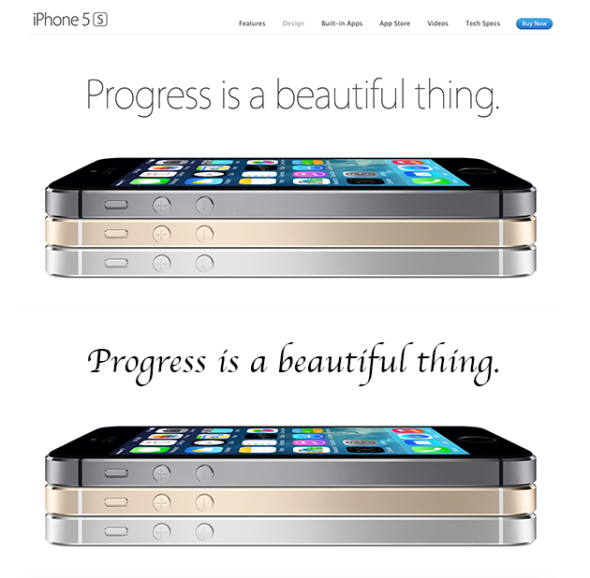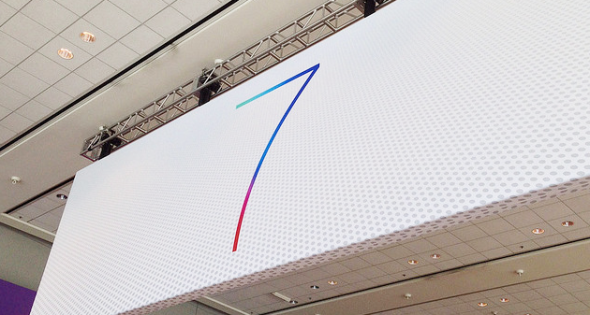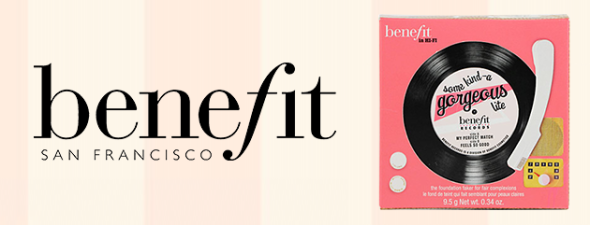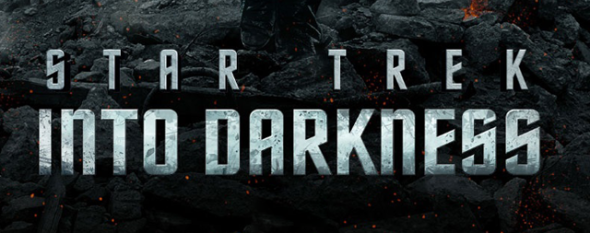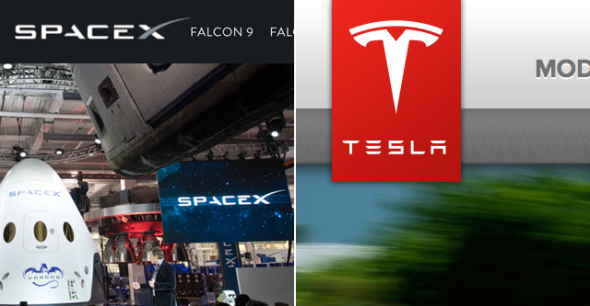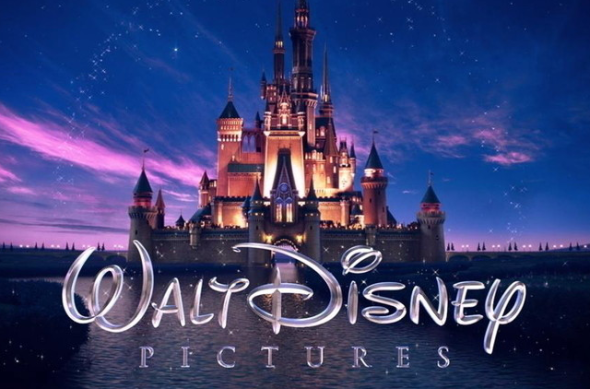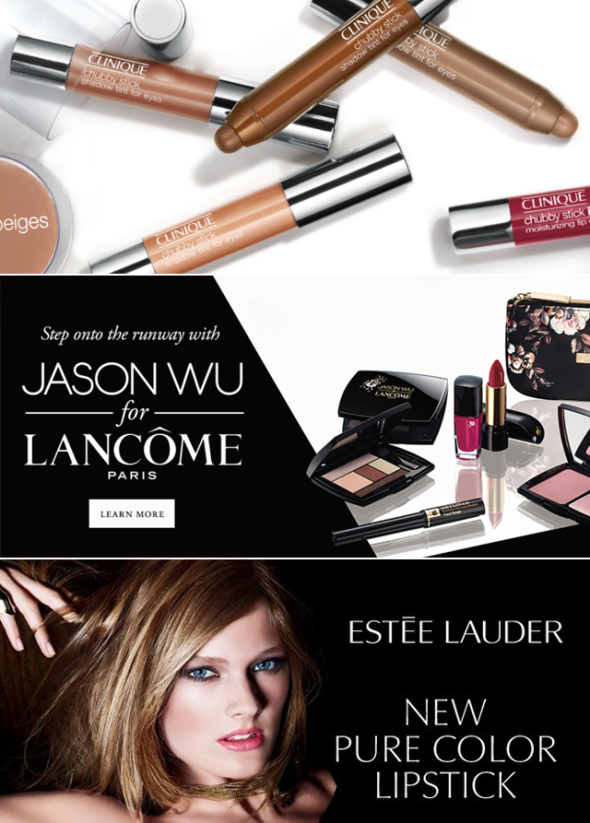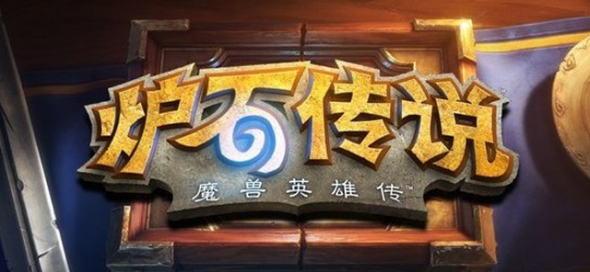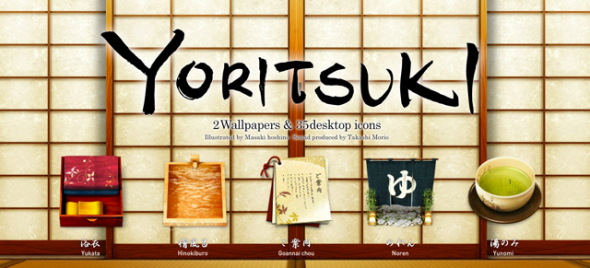
当我们拿到一款产品的包装或者登入了一个网站的时候,你是否会有意或者无意地留意到属于这个产品的特定的字体设计或者使用,从而影响到你对这个产品最直观的感受。精致、优雅、科幻、古典或者是觉得粗糙难看呢?
比如当我把苹果网站上 iPhone 的字体换掉以后,你一定或多或少的察觉到了什么不一样的地方,也许你无法表达出来或者无法说出究竟是哪里出了问题,但这潜意识的感受正是不同字体风格传递给用户的直观感受所造成的。因此在给一个产品选择或者设计字体的时候,除了你需要考虑其易读性,一定也需要考虑这款字体是否能准确地传递给消费者或用户属于这款产品的独特气质。
A.现代
现代风格字体多为无衬线字体,这类字体除本身文字的比划之外缺少装饰性的元素,风格较简约。
WWDC 2013前夕,即便在 iOS 7 并未对外界正式发布之前,但是通过会场的海报人们都清楚地意识到,iOS 7 的风格一定带来了极大的转变。Helvetica Neue 风格非常现代,似乎暗示着苹果将在 iOS 7 中完全剔除过去人们陈旧的审美,取而代之的是更为现代的视觉风格,而在后来的大会上 iOS 7 的最终发布也证实了这种观点。
B.复古
化妆品品牌 Benefit 诞生于美国上世纪 70 年代这个自由奔放的时代,而创始人之一的姐姐 Jean Ford 刚好主修艺术,她十分懂得如何包装她们的品牌。Benefit 的包装和字体颇具复古风,比如留声机造型的包装盒。衬线字体的 logo 具有较强的装饰性,字母的转角处线条柔和,更具流线形的字母 f 使 logo 显得更生动有趣,搭配留声机造型内部的连笔手写体,一股浓浓的复古风扑面而来,见到如此有趣又漂亮的包装盒,难怪让很多女性爱不释手。
C.科幻
电影星际迷航的海报上的字体就属于这种类型。实际上我们经常会在一些科幻电影的海报或者网站上见到这种类型的字体。科幻风格的字体风格普遍比较硬朗和锐利,通常有过渡比较直接的折角。
作为钢铁侠原型的传奇人物,Elon Musk 创办的几家公司的 logo 字体设计也类似。除了具有比较硬朗的线条之外,Tesla 和 SpaceX 的 logo 去除了一些连接的比划从而使字形显得更加抽象和神秘,真是科技感十足的公司啊!
D.梦幻
迪士尼的字体就属于这种风格,粗细不一的比划和大小不同的字母具有非常强烈的节奏韵律感,字母划出的曲线像翩翩起舞的丝带,也像魔棒划出留下的痕迹,使人充满想象。
E.女性
女性化风格的字体经常可以在化妆品品牌中看见,她们通常字体纤细、秀美,线条流畅,字形有粗细等细节变化,显得有韵律或通过装饰性元素和字体结合。因为衬线字体天生具有衬线这种可装饰性元素,因此很多女性化风格的字体会选用衬线字体,并以此为基础进行修改,比如 LANCOME 的 logo 字体。
F.趣味
具有趣味性的文字可以使用产品中的某些元素和文字进行创意性的结合,比如炉石传说的字体设计,巧妙的运用魔幻一样的“漩涡”和石头下半部分的“口”结合起来,虽然炉石传说几个字在风格上是保持一致的,但是每个文字的折角并没有刻意地将大小或角度保持标准一致,这样的非规律性做法也增加了字体的趣味感,让用户觉得这款游戏一定会具有可玩性。
G.文化
Yoritsuki 的字体设计使用了毛笔书法的笔触书写的方式,将墨这种元素融入到了字体当中,这种东方文化中特有的东西,使得 Yoritsuki 这款 App 的风格显得非常鲜明,即使在你还没有打开这个 App 的时候,你就已经能大概知道里面会是什么样子的了。
结语:论字体风格的话,远远不止上文罗列出来的,并且很多时候,一款字体可以同样适用于多种不同风格之间。然而如何使用一款合适的字体准确地将产品气质传递给用户,这正是设计师应该考量的东西。